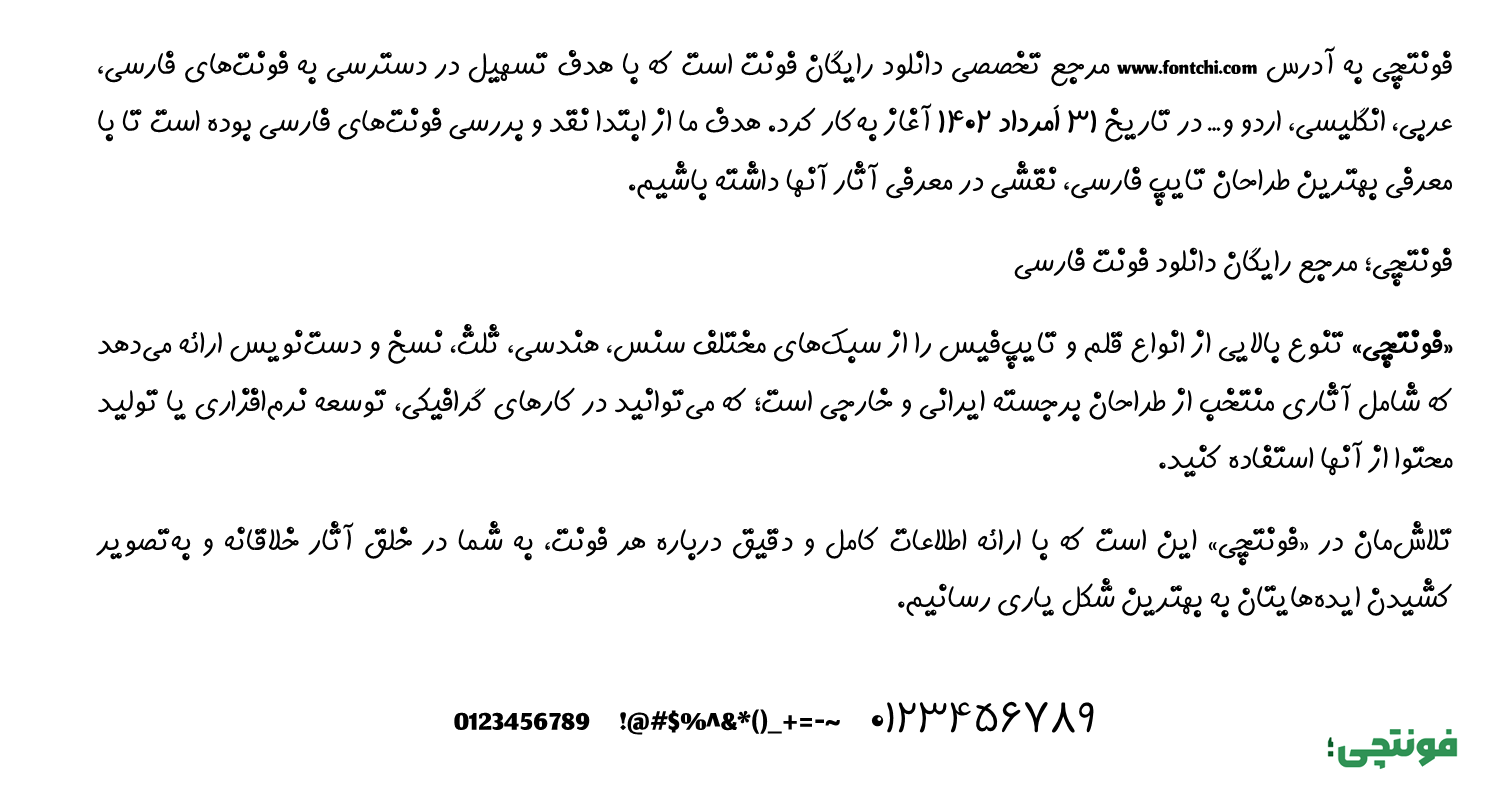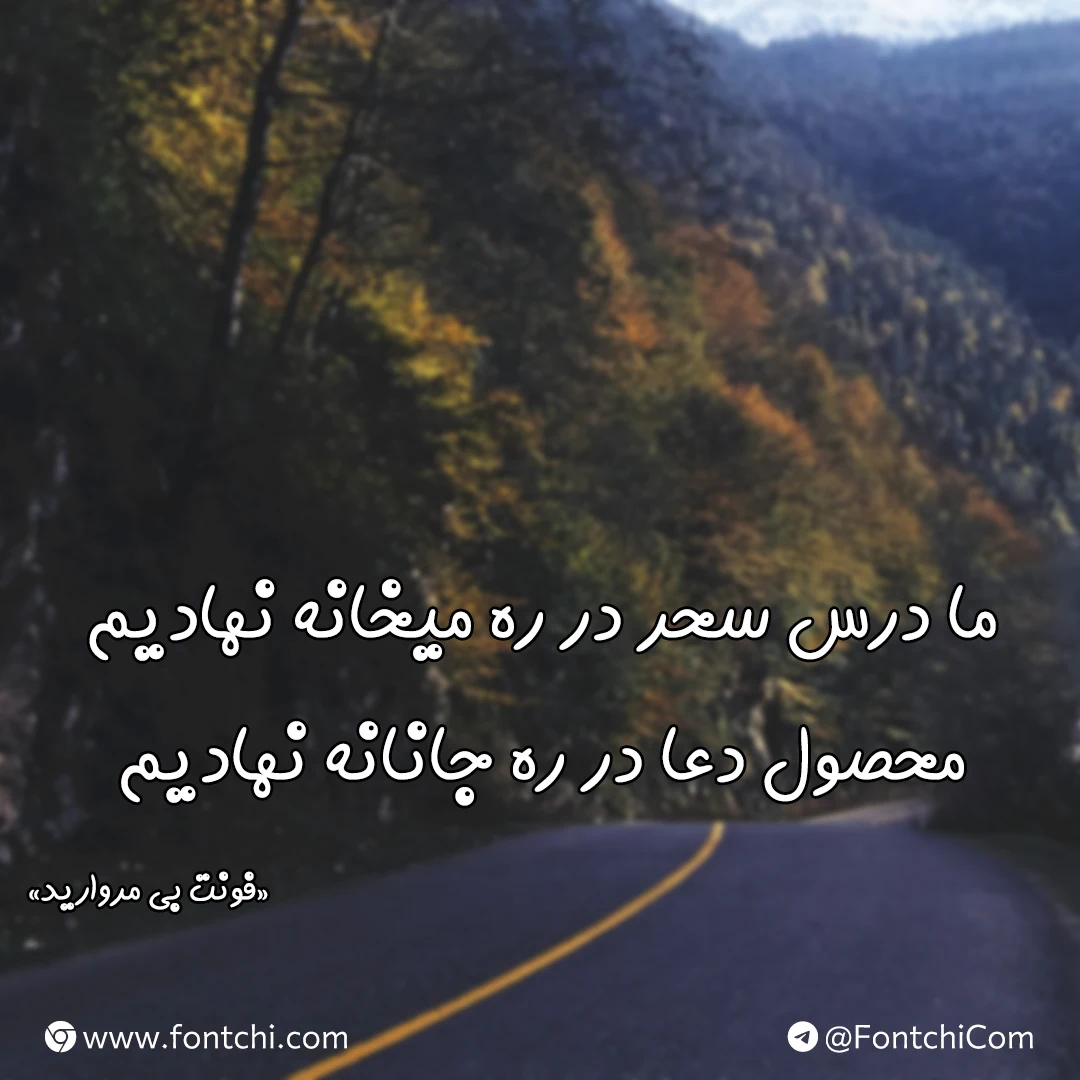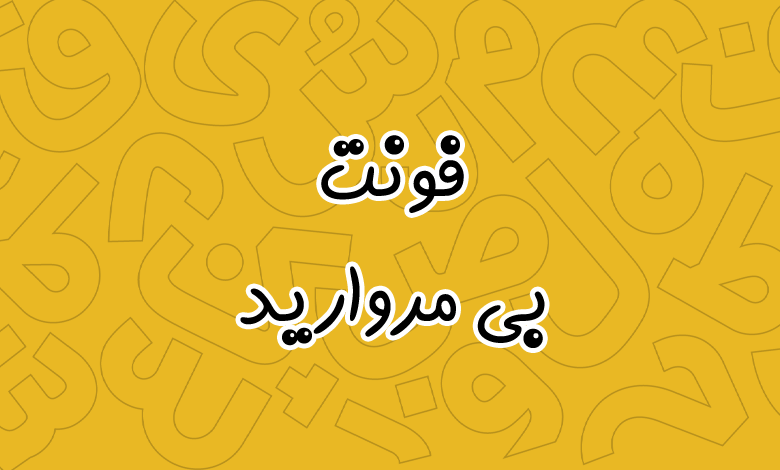
فونت بی مروارید (B Morvarid)
فونت بی مروارید (به انگلیسی: B Morvarid) از فونتهای محبوب و کلاسیک پارسی است که توسط برنا رایانه طراحی شده و بخشی از سری فونتهای بی مانند B Nazanin محسوب میشود. این فونت با ظاهری فانتزی برای استفاده در متون کوتاه و بلند، بهویژه عناوین کاربردی است.
فونت مروارید از زبان فارسی پشتیبانی کاملی دارد. برای زبان عربی نیز تا حدودی بهینه شده و پشتیبانی از زبان انگلیسی نیز بر اساس فونت پیشفرض سیستم پیادهسازی شده است. در ادامه، به بررسی سبک، طراحی، کاربردها، ویژگیهای این فونت فارسی میپردازیم.
فونت بی مروارید در اصل جزو فونتهای دستنویس طبقهبندی میشود، اما به دلیل ظاهری نسبتا رسمی، کلاسیک و فانتزی این ویژگی فونت زیاد به چشم نمیآید. سبک آن ترکیبی از خطوط منحنی و نرم است که حس ظرافت و زیبایی را القا میکند، شبیه به دستخطهای سنتی اما با ساختاری مدرن شده است.
این فونت نه خیلی فانتزی است و نه کاملا sans-serif یا serif؛ بلکه به عنوان یک فونت عادی برای متنهای رسمی و هنری طبقهبندی میشود. برخلاف فونتهای ساده مانند B Mitra، بی مروارید ظاهری جذابتر و پویاتر دارد که آن را برای کارهای خلاقانه ایدهآل میکند.
فونت بی مروارید توسط برنا رایانه طراحی شده است. در طراحی این قلم فارسی از خطوط منحنی و زیبا با تمرکز بر خوانایی بالا، حتی در اندازههای کوچک تمرکز شده است. حروف فارسی در آن به صورت پیوسته و طبیعی طراحی شدهاند، که این امر آن را از فونتهای مکانیکی متمایز میکند. این فونت برای ایجاد ظاهری جذاب در متنها ساخته شده و از سبک خاصی الهام گرفته که باعث پرکاربرد شدن آن شده است. در مقایسه با فونت Far.Morvarid (که نسخهای مشابه اما بامزهتر است)، بی مروارید رسمیتر و حرفهایتر به نظر میرسد.
این فونت برای کارهای رسمی و آموزشی بسیار مناسب است، مانند طراحی بنرها، پوسترها، کارتهای تبریک، لوگوها و محتوای گرافیکی. همچنین در طراحی وبسایتها، کتابها و مجلات پارسیزبان استفاده میشود، زیرا خوانایی بالایی دارد و میتواند در متنهای طولانی بدون خسته کردن چشم به کار رود.
اغلب برای پروژههای خلاقانه مانند طراحی تصاویر یا محتوای تبلیغاتی استفاده میشود. به دلیل سبک دستنویس، برای کارهای هنری و غیررسمی نیز کاربرد دارد، اما بیشتر در زمینههای رسمی آموزشی برجسته است.
- خوانایی بالا: حروف به گونهای طراحی شدهاند که حتی در اندازههای کوچک یا چاپی، واضح باشند.
- طراحی کلاسیک و زیبا: با خطوط منحنی، ظاهری جذاب به متن میبخشد و حس حرفهای ایجاد میکند.
- وزن فونت: عمدتاً در وزن Regular (معمولی) عرضه میشود، بدون نسخههای bold یا italic رسمی، اما میتوان آن را برای نیازهای مختلف تنظیم کرد.
فونت بی مروارید عمدتا برای زبان فارسی طراحی شده و از تمام حروف و کاراکترهای پارسی پشتیبانی کامل میکند. همچنین، به دلیل پایه اسکریپت عربی، از زبانهای عربی، اردو، پشتو، کردی (سورانی) و دیگر زبانهای مبتنی بر الفبای عربی پشتیبانی میکند. برای زبان انگلیسی، از کاراکترهای Basic Latin و Latin-۱ Supplement پشتیبانی دارد، اما تمرکز اصلی روی زبانهای راستبهچپ است.
همانطور که اشاره شد از این فونت بیشتر برای کارهای گرافیکی استفاده میشود. برای استفاده در محیط وب سایت میتوانید این فونت را برای اسلایدرهای تصویری تعریف کنید که برای سایتهایی در حوزه کتاب و فروش محصولات آموزشی گزینه خوبی محسوب میشود؛ بهویژه در حوزه کودک و نوجوان.